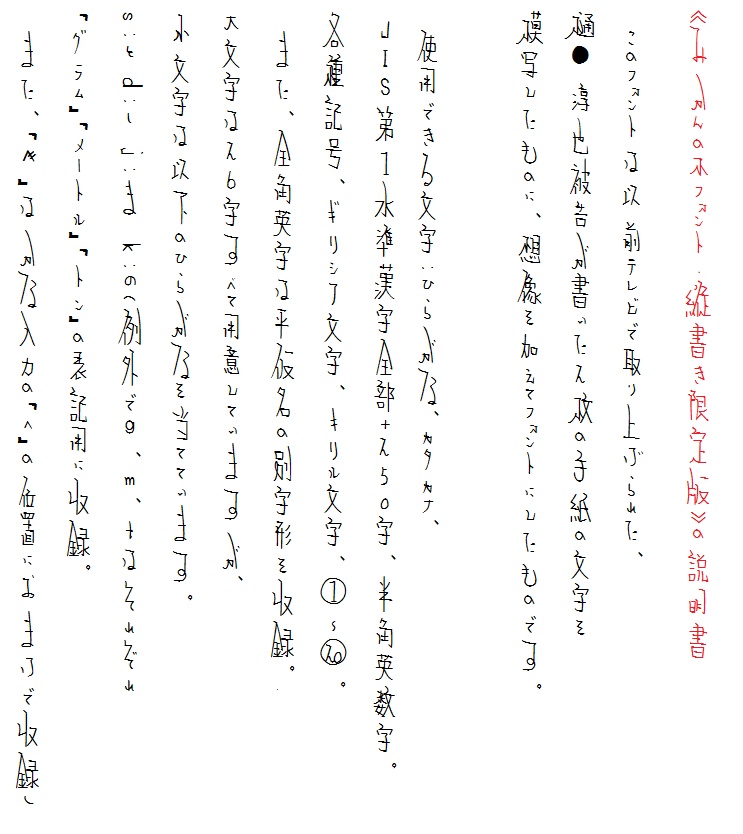
みかんの木フォント・バージョン2(横書き限定版・縦書き限定版)
《みかんの木フォント・バージョン2》の説明 このフォントは以前テレビで取り上げられた、樋●淳也被告が書いた 2枚の手紙の文字を模写したものに、想像を加えてフォントにしたものです。 使用できる文字(縦・横共通):ひらがな、カタカナ、JIS第1水準漢字全部+250字、 半角英数字、各種記号、ギリシア文字、キリル文字、①~⑳。 横書き限定版のみ:半角カタカナ・主要な発音記号。 縦書き限定版のみ:元号の合字、㈱、㊞、㎞などの主要なもの。 また、縦・横共通で全角英字には平仮名の別字形を収録しています. s:と d:し j:ま k:の (おまけでかな入力の「へ」の位置に二本線の入った「へ」を収録) 重要:縦書き限定版をワードパッドで使用すると 特に漢字から次の文字について文字同士が 重なってしまう事態になっています。 その場合は間にスペースを挟んで対応してください。 ペイント機能のテキストでは問題ありませんでした。 ※これは「仕様」ですのでご理解のほどをよろしくお願いします。 ライセンス:このフォントは同人誌などにもお使いいただけますが 無保証とさせていただきますので充分ご理解のうえご使用ください。 また、文字の大きさの関係上、文字サイズを少し大きめに設定してお使いください。